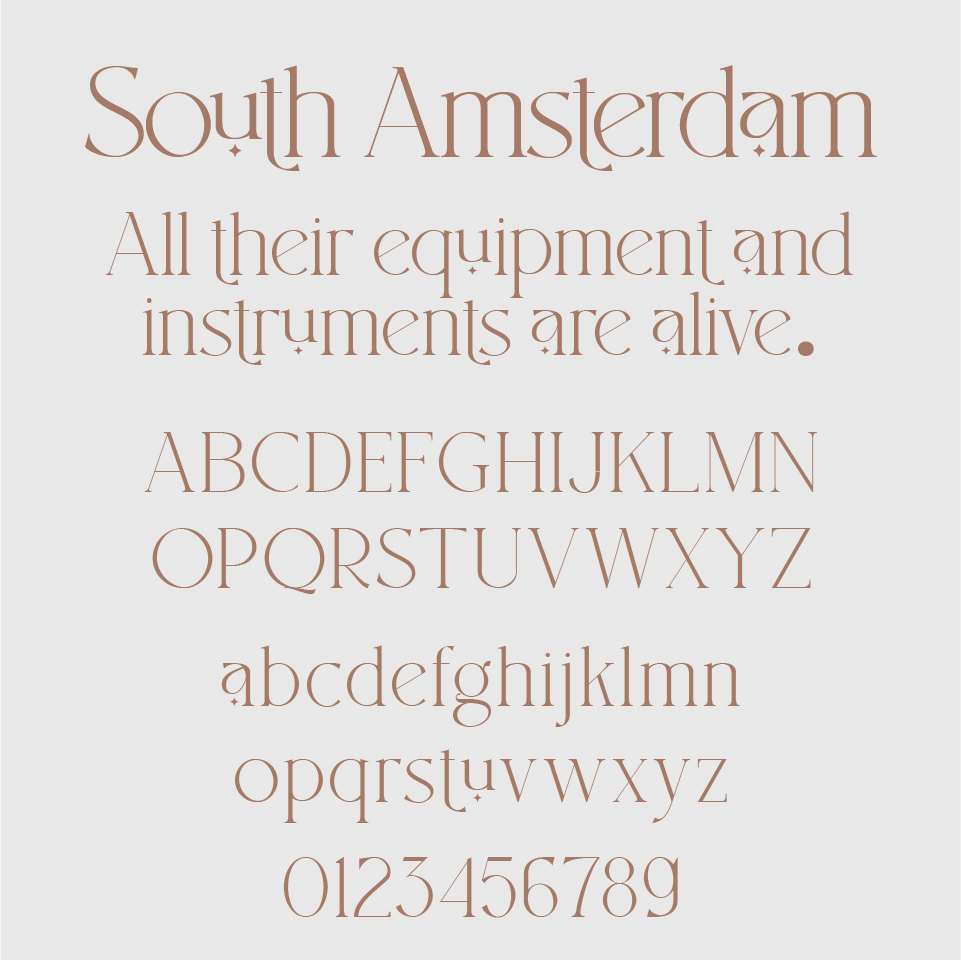
South Amsterdamフォントは、繊細で洗練されたセリフ体に、小さな星のような装飾がちょこんと添えられた、ロマンチックな雰囲気のフォントです。どこか物語の始まりを思わせるような優雅さがあります。
可愛らしさと上品さが共存するデザインで、コスメやジュエリーなどのビジュアルにも似合いそうな雰囲気です。装飾的でありながら読みやすく、ちょっと特別感を出したいときに使いたくなるフォントです。